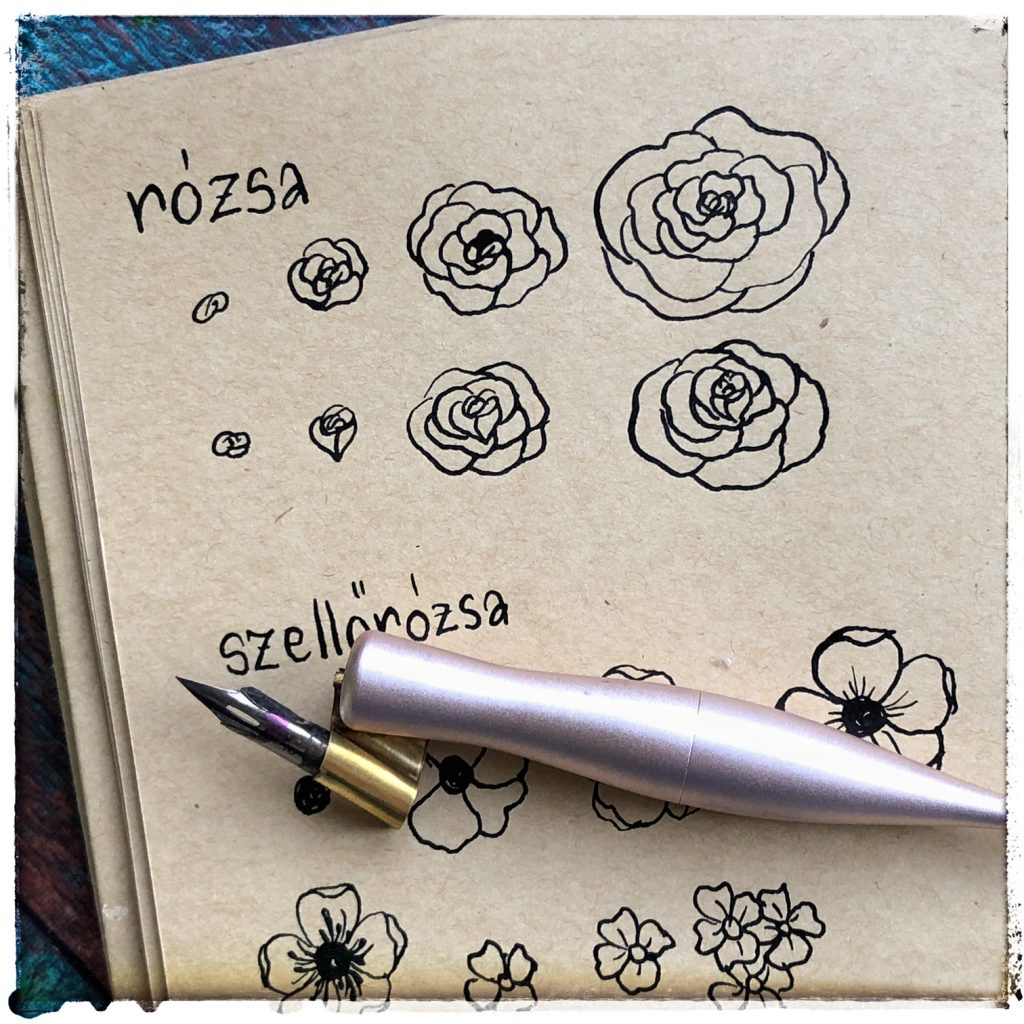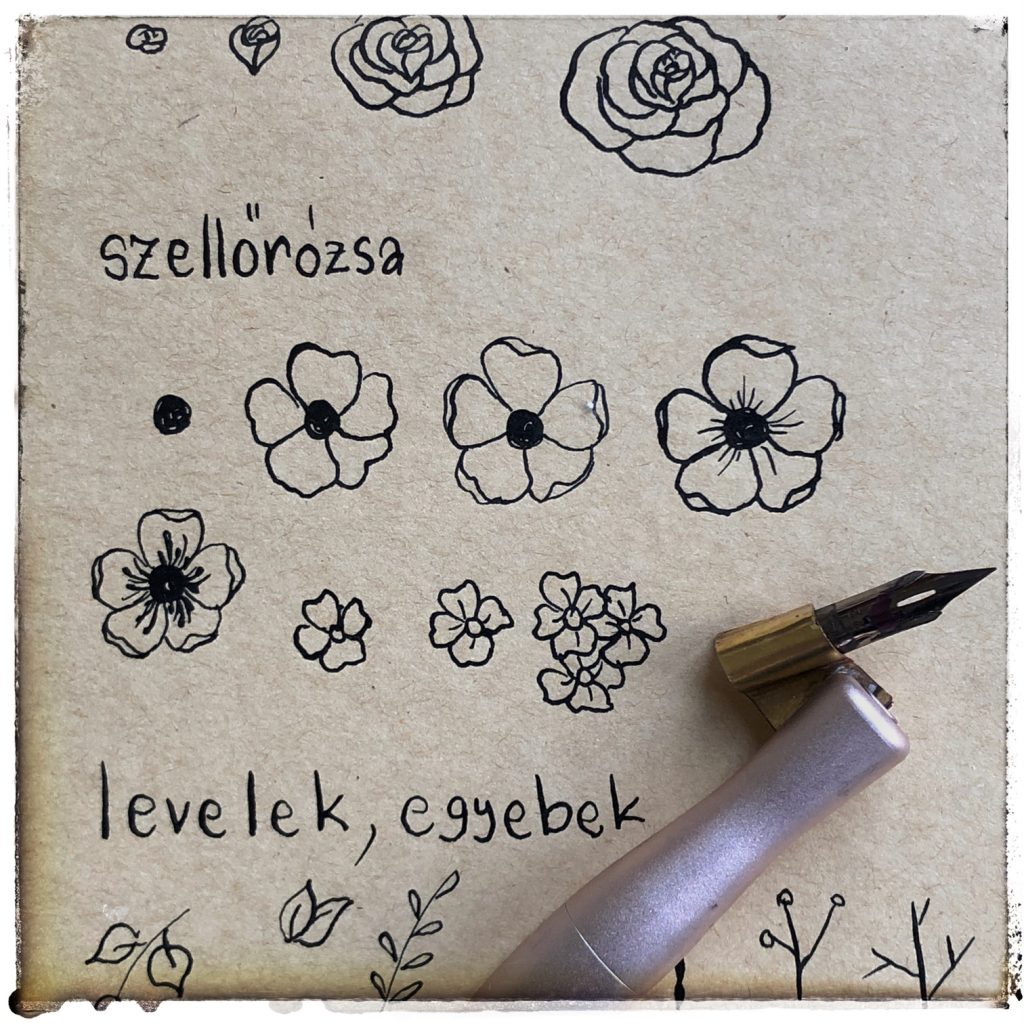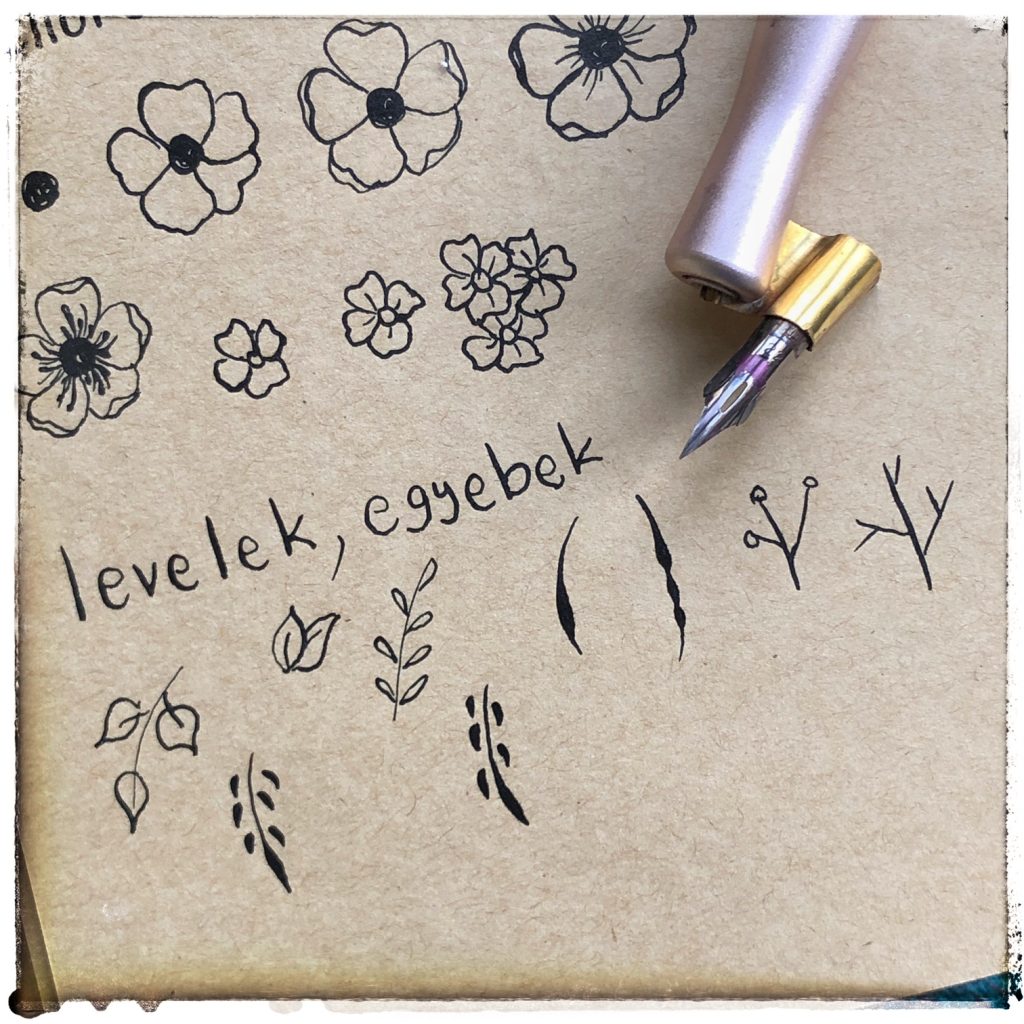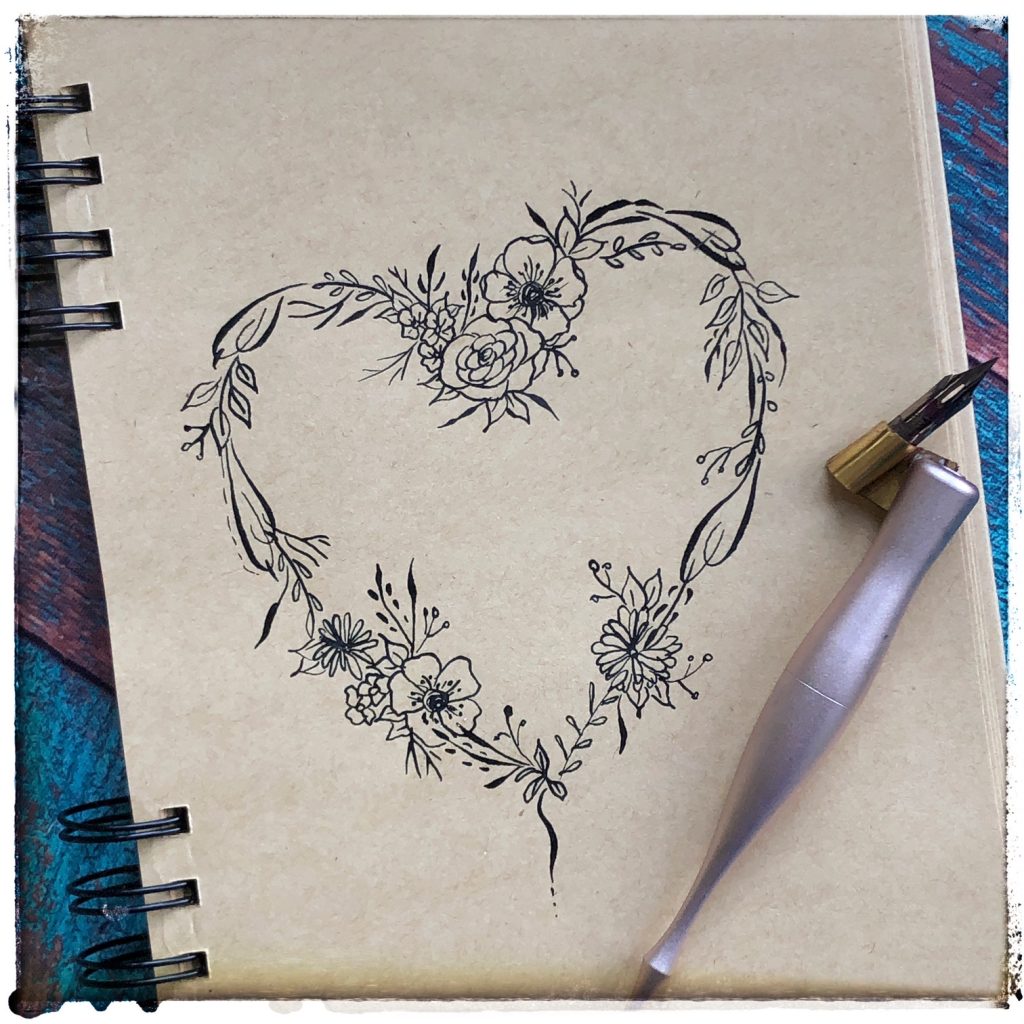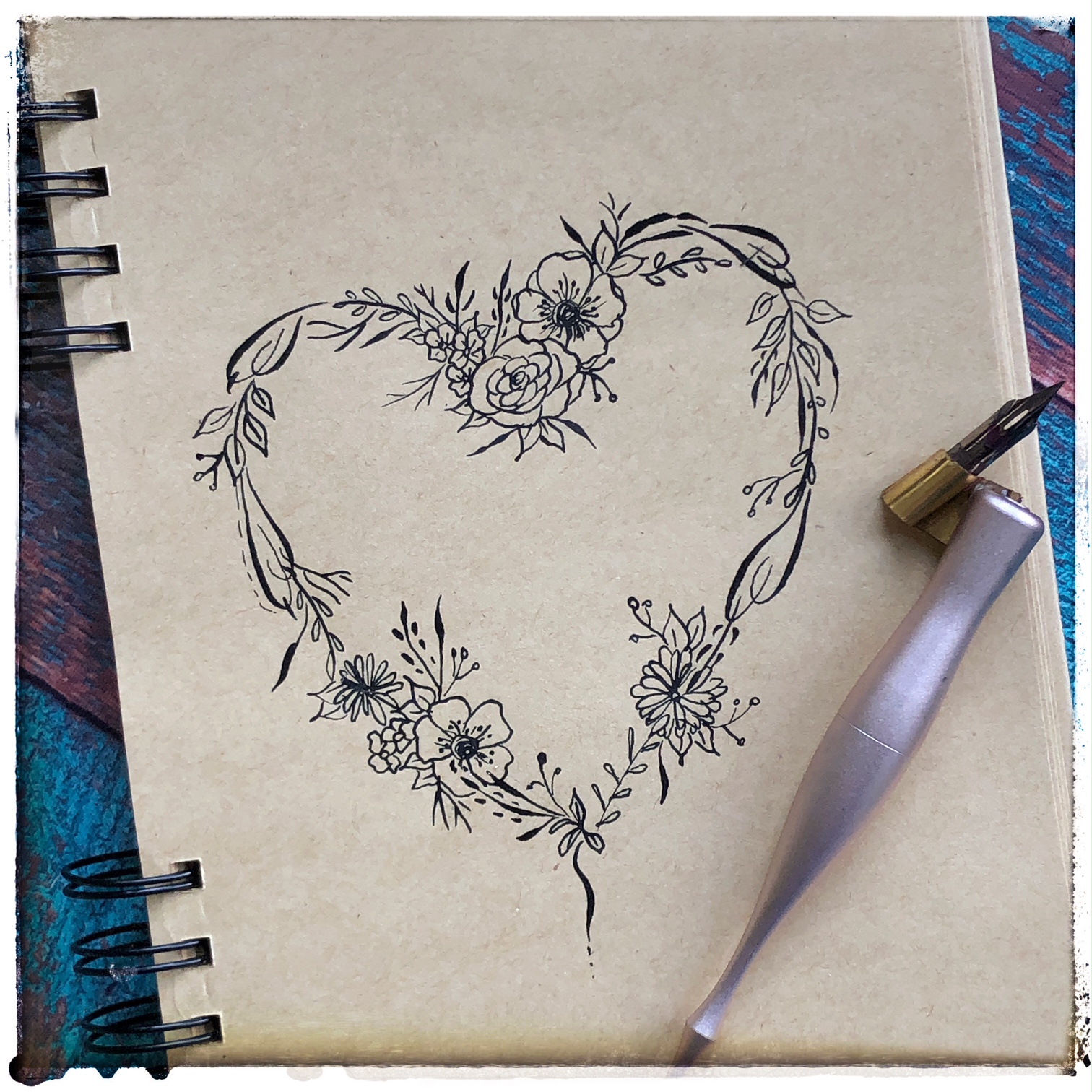
Virágok mártogatós tollal
Mártogatós tollal nemcsak írni lehet, hanem rajzolni is. Nagyon egyszerű és jól kiegészítheti a kalligráfiánkat.
virágok mártogatós tollal
Egy előző posztban bemutattam, hogyan is tudod használni a mártogatós tollat. Azonban a mártogatós tollat nemcsak írásra tudod használni, hanem lehet vele rajzolni is, virágokat, leveleket, ágakat. Ezzel fel tudod dobni a kalligráfiád, ki tudod tölteni az írás körül lévő űröket. A rajzoláshoz nincs szükséged másra, mint papírra, mártogatós tollra, simán használhatod ugyanazt a hegyet, mint íráshoz és természetesen tintára. Az én választásom a Moblique tollszár, Hunt 101 tollhegy, Kuretake sumi ink, Clairefontaine füzet. Nézzük is lépésről lépésre, hogyan tudod megrajzolni virágokat, leveleket.
Rózsa rajz
Kétféle rózsát mutatok meg, igazából ez két nézete a rózsának. Az egyik szemből, a másik oldal nézetből ábrázolja.
Az első sor mutatja a szembe verziót. Először rajzolsz két mini „c” formát, ami egymásba fonódik. Utána kisebb c formákat rajzolsz e köré (2.kép). Majd ahogy növekszenek a szirmok tegyél bele egy kis hullámot (3. kép). Akár itt is megállhatsz, de növelheted tovább, ahogy a 4. képen látod. Itt már egészen nagyok a rózsa szirmok.
A második sorban láthatod az oldal nézetet. Ez is a „c” formákkal kezdődik. Azonban először nem köré húzod a több c vonalat, hanem rajzolsz egy szívecske szerű formát (2. kép). Ezután jöhet a többi szirom, itt már jöhet bele némi hullám, illetve arra figyelj, hogy a felső szirmok legyenek kisebbek, helyezkedjenek közelebb a virág közepéhez, mint az alsók. Ezzel tudod megteremteni azt a hatást, hogy oldalról látjuk a rózsát (3. kép). Itt is te döntöd el, hogy mekkora rózsát rajzolnál, tovább tudod növelni még nagyobb szirmokkal (4. kép).
Ilyen egyszerű, és már kész is az első virágod. 😀
rózsa mártogatós tollal
Szellőrózsa rajz
Nézzük a következő virágot, ez a szellőrózsa, angol nyelvterületen nagyon népszerű virág, anemone a neve. Első lépés, hogy rajzolsz laza köröket. Ez lesz a virág bibéje, utána rajzolj 5 szirmot köré. A szirmok tetejébe legyen egy hullám (2. kép). A következő lépésben ezt a hullámot zárd le egy párhuzamos hullámmal (3. kép). Majd húzz vékony vonalakat a szirmokba a bibétől kezdve a széle felé, de ne érje el azt! A középső legyen a leghosszabb, majd a többi egyre rövidebb (4. kép). Ezután jöhet néhány pötty a bibe körül, amit szintén egy vékony vonallal kösd össze a bibével (2. sor 1. kép).
Ennek van egy egyszerűbb és kisebb verziója. Ezt használhatod önállóan vagy hármasával, ezeket érdemes az üres helyek kitöltésére használni. Szóval rajzolsz egy apró kört, majd e köré jöhet 4 szirom (2. kép). Hasonló, mint amit a szellőrózsánál használtál. A szirmokba húzz egy-egy vékony vonalat, ezzel is tudod még valóságosabbá tenni a virágod (3. kép). Ezután rajzolhatsz egymás mellé többet is, lényeg, hogy szorosan legyenek egymás mellett. A szirmok takarják egymást (4. kép).
szellőrózsa mártogatós tollal
Levelek és egyéb kitöltő elemek rajzolása
Meg is vannak a virágok, azonban ahhoz, hogy egy szép kompozíciót kapj, szükségesek a levelek és egyéb kitöltő elemek. Kezdjük a levelekkel. Érdemes magad felé rajzolni, szerintem úgy könnyebb. Szóval húzz egy szárat, majd mintha egy szívet rajzolnál, húzz magad felé egy ívet az egyik oldalon, majd a másikon. Ha hosszabb ágat húztál, akkor még több levelet is tudsz ugyanígy rajzolni (bal felső kép).
Aztán tudsz húzni klasszikus levelet, ami 2 hullám vonal egymás felé fordítva. Ezt úgy tudod még valóságosabbá tenni, hogy rajzolsz alá egy másik levelet úgy mintha eltakarná. Ezt úgy éred el, hogy az egyik hullám csak részben látszik, míg a másik teljesen ( felső sor 2. kép). Itt is érdemes egy középső vonallal, a főérrel még feldobni.
A következő egy nagyon egyszerű leveles ágacska. Szintén egy vonallal indul, amire csepp formájú leveleket rajzolok. A leveleket lehet egymással szemben rajzolni, vagy felváltva is. (felső sor 3. kép)
Felső sor 4. kép egy búzakalász. Ezt mindig magad felé húzd, kezd egy vékony vonallal, majd kis vastagítás jön, úgy, hogy rányomod jobban a tollat, mint a kalligráfiánál. Végül újra vékonyítsd el a vonalat, és már kész is. Mellette van ennek egy variációja, amikor több kis ilyen vastagítást rajzolsz egymás után.
A felső sorban az utolsó 2 kép ágacska variációk. Az utolsó egy sima ágacska, az előtte lévő pedig szintén egy ágacska, csak körök vannak a végén, ami a bogyókat szimbolizálja.
Az alsó sorban megint egy búza variációt találsz. Ez is úgy indul, hogy egy vékony vonalat húzol, melyet a végén vastagítasz és vékonyítasz. Majd búzaszemeket rajzolsz úgy, hogy egy cseppet húzol, az elején rányomod, majd szinte azonnal felengeded a mártogatós tollat. Ezt is lehet egymás mellett húzni, vagy felváltva.
levelek, egyebek mártogatós tollal
Virág kompozíció mártogatós tollal
Most már meg vannak az alap elemek, rakjuk össze egybe, egy kompozícióba. Rajzolj halványan egy szívet ceruzával. A csücskébe rajzoltam egy rózsát, ez kicsit kitakarja a szellőrózsát, illetve 3 kis virágot. Köré rajzoltam a kitöltő elemeket: leveleket, ágakat, búzakalászokat. Utána jöttek a kalligráfiában használt alsó hurkok, csak ne zárd be őket, és fordítsd egymással szembe őket. Aztán jöhetnek az újabb ágak, levelek, illetve virágok, és már kész is az első mártogatós toll kompozíciód. Persze ez csak egy ötlet, számos variációban kipróbálhatod.
virágok mártogatós tollal